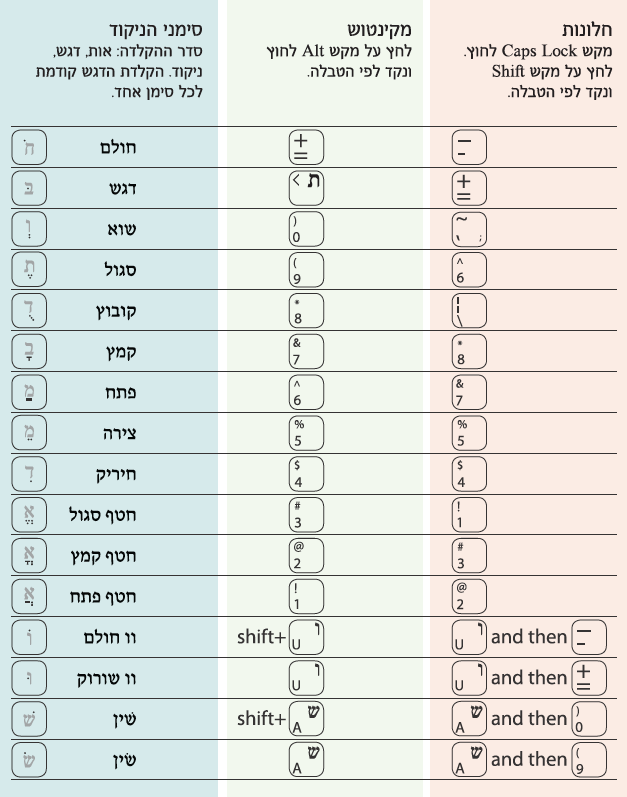
פונטים
מנוקדים לדפוס הם פונטים בפורמט OpenType Pro ושם הפונט תמיד יתחיל בצמד האותיות "MF”. היתרון
המרכזי של פורמט OpenType Pro החדשני
הוא המיקום המדויק של הניקוד בהתייחס
לצורת האות. מיקום הניקוד מתוכנת כך שהוא מוגדר על פי המרכז האופטי של האות ולכן האות המנוקדת נראית במיטבה.